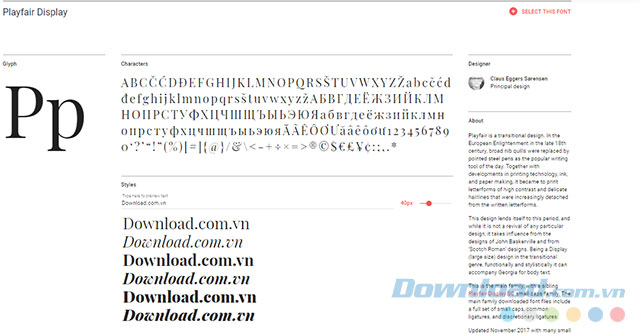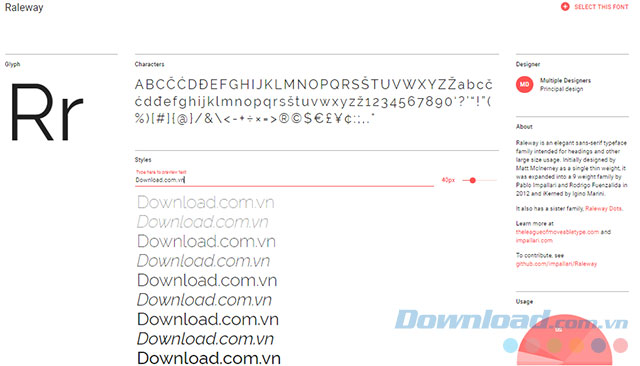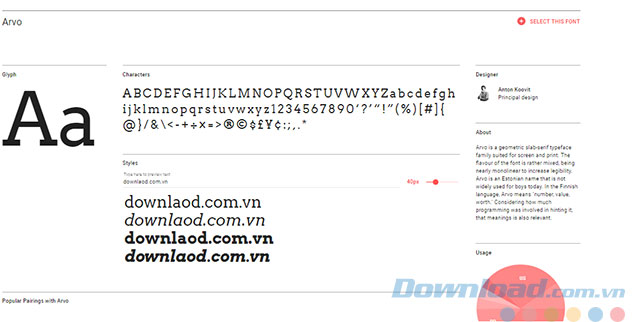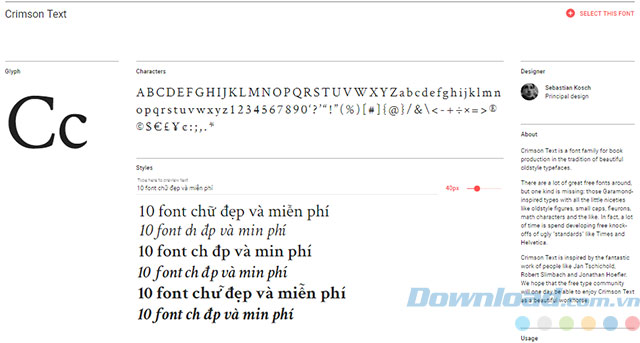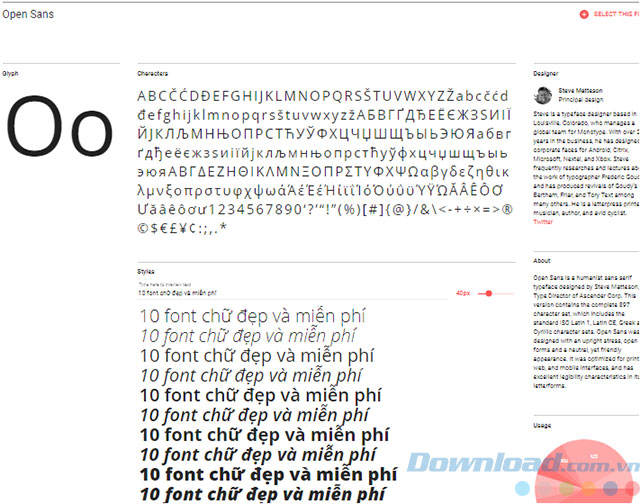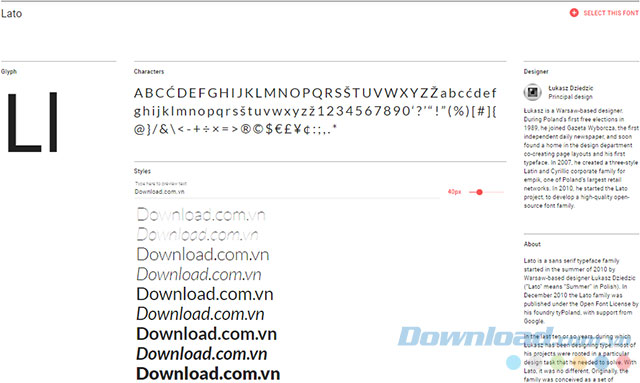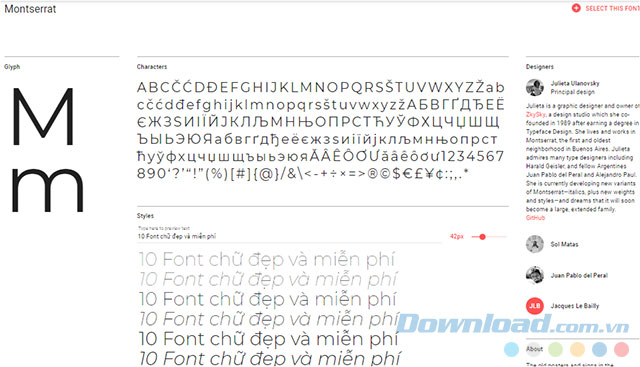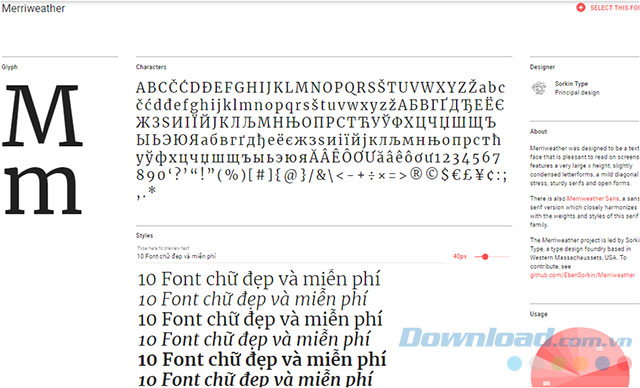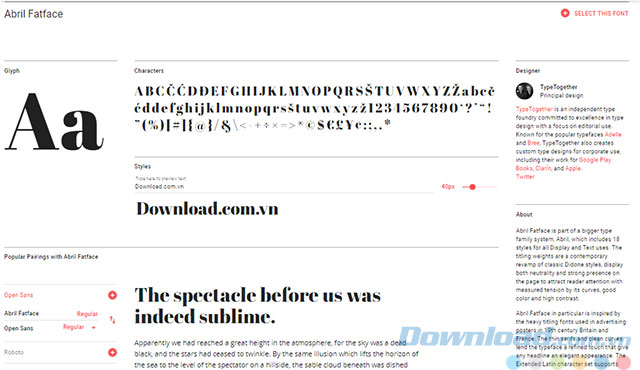
Top Font chữ cực đẹp và miễn phí trên Google
Khi soạn thảo văn bản chúng ta thường sử dụng những font chữ có sẵn từ Windows như font VNI, font TCVN3... hay các kiểu có sẵn trong Microsoft Office. Nếu bạn cảm thấy nhàm chán với nó và muốn thay đổi thì hãy thử với những font chữ đẹp được cung cấp miễn phí bởi Google dưới đây.
10 font chữ đẹp và miễn phí từ Google
1. Playfair Display
Playfair Display được xây dựng dựa trên phông chữ serif, nó được bắt đầu từ cuối thế kỉ 18 tại Châu Âu khi mà những cây bút ngòi đậm được thay thế bằng loại bút thép sắc nhọn.
Kiểu chữ này được xem là trái ngược hoàn toàn với phông chữ Times New Roman khi nó đem lại cho chữ viết một nét rất duyên dáng và nữ tính.
Nếu bạn sử dụng font chữ này cho tiêu đề thì sẽ giúp cho văn bản của chúng ta trở nên đẹp hơn, đặc biệt là khi ta kết hợp nó với màu pastel.
Playfair Display
2. Arvo
Arvo là một kiểu chữ hình học với sự kết hợp giữa cổ điển và hiện đại. Nếu Arvo Regular là một phiên bản hiện đại với nét chữ slab serif, thì Arvo Bold lại có nét chữ dày hơn và nhọn hơn.
Font chữ này được sử dụng làm tiêu đề trong nhiều bài thuyết trình cho việc kinh doanh và các doanh nghiệp. Nó sẽ giúp cho văn bản của chúng ta trở nên đẹp hơn khi cho kích thước của chữ to lên và kết hợp với một số màu phù hợp với nội dung của bài viết.
Arvo
3. Crimon Text
Với một vẻ đẹp giản dị, Crimon Text được sử dụng làm tiêu đề và phụ đề cho các bài thuyết trình mang phong cách cổ điển.
Đây là một phiên bản hiện đại của các phông chữ truyền thống và được lấy cảm hứng từ kiểu chữ Garamond. Nó được thiết kế trông đẹp hơn trên màn hình và các trang web. Font chữ này cũng có thể thay thế cho Times New Roman khi bạn cảm thấy nhàm chán.
Crimon Text
4. Open Sans
Trước khi thực hiện một bài thuyết trình chuyên nghiệp, cần tránh viết những đoạn văn dài, ngay cả khi những danh sách với gạch đầu dòng cũng làm cho chúng ta có cảm giác nhàm chán. Nếu như bạn bắt buộc phải viết những đoạn dài vì nó cần thiết cho văn bản của mình, hãy thử sử dụng font chữ Open Sans.
Đây là một phông chữ dạng sans serif và thuộc phân loại Humanist (là một phân loại của các kiểu chữ). Font chữ này được sử dụng trong những văn bản có đoạn văn dài vì nó dễ đọc dù cho kích thước chữ nhỏ.
Phiên bản semibold hoạt động tốt như một tiêu đề vì nó có nét chữ dày nhưng nhỏ hơn chữ in đậm.
Open Sans
5. Lato
Đây là font chữ được một tập đoàn đặt làm riêng nhưng sau đó thì tập đoàn này lại quyết định cung cấp miễn phí cho mọi người sử dụng nó.
Lato theo nghĩa tiếng Ba Lan là "mùa hè", phông chữ này được thiết kế mang nét tươi vui với các chi tiết bán nguyệt đầy tinh tế nhưng vẫn đem lại tính chuyên nghiệp. Chính vì vậy mà nó được sử dụng trong những đoạn văn dài hay làm tiêu đề cho các bài thuyết minh.
Lato
6. Montserrat
Montserrat sẽ giúp đem lại một sự trẻ trung nhưng vẫn chuyên nghiệp cho bài thuyết trình của bạn. Phông chữ này thường được sử dụng cho các landing page trong những startup về công nghệ.
Font chữ này được lấy cảm hứng từ các áp phích của những cửa hàng cũ của khu phố Montserrat ở Buenos Aires nên nó mang tính truyền đạt rất cao. Nhờ thiết kế hình học nên phông chữ này kết hợp rất tốt với kiểu chữ sans-serif.
Montserrat
7. Merriweather
Merriweather được xây dựng nhằm tối ưu hóa nội dung trên màn hình và là một phông chữ serif truyền thống nhưng nó lại rất phóng khoáng. Các dạng form chữ cũng được cô đọng và tạo ra nhiều khoảng trống hơn cho các chữ cái.
Merriweather
8. Abril Fatface
Đây là một phần của họ Abril với 18 kiểu chữ khác nhau, từ phiên bản Display cho đến Text. Phiên bản Fatface không dành cho hầu hết mọi người, trên thực tế nó được sử dụng cho những người có phong cách rất đặc biệt.
Abril Fatface có nét chữ dày với phần đuôi rất mảnh, sự kết hợp này làm cho font chữ nên độc đáo và gây ấn tượng khi xuất hiện trên màn hình. Khi sử dụng nó cho những bài thuyết trình sẽ đem lại cảm giác tươi vui nhưng vẫn giữ được phong cách chuyên nghiệp. Nếu muốn văn bản của mình trở nên nổi bật thì hãy dùng phông chữ này làm tiêu đề.
Abril Fatlace
9. Ubuntu
Đây được xem như là một phiên bản mang phong cách riêng của Open Sans và cũng là kiểu chữ sans-serif, thuộc loại Humanist. Phông chữ này được đặt tên là Ubuntu vì Canonical là công ty đứng sau Ubuntu Linux tài trợ để phát triển nó.
Không có những cạnh tròn đối xứng như Open Sans mà Ubuntu lại uốn cong từ một cạnh và biểu hiện rõ điều này qua các chữ như "u" và "n".